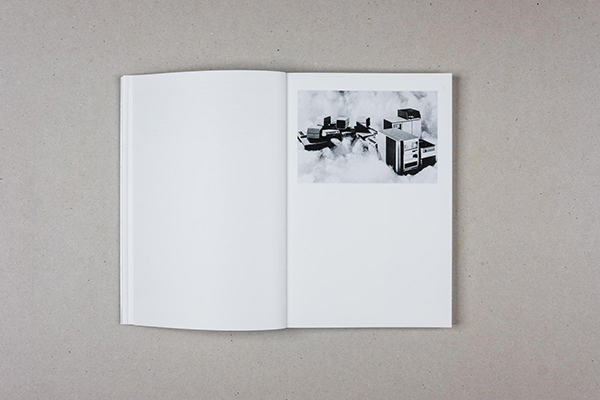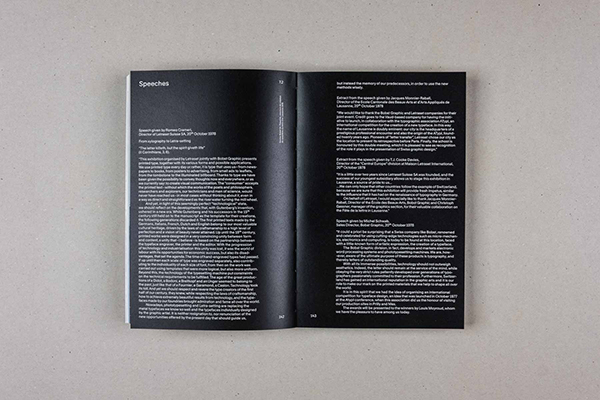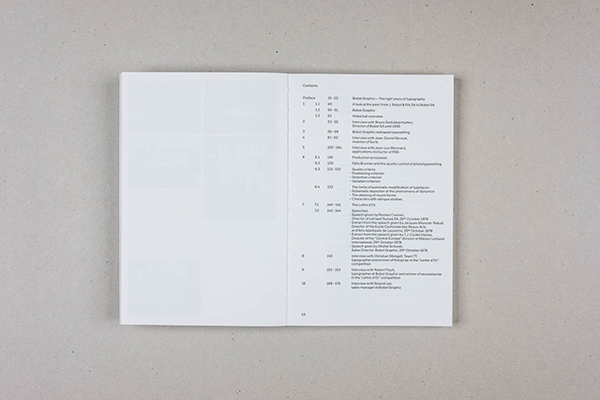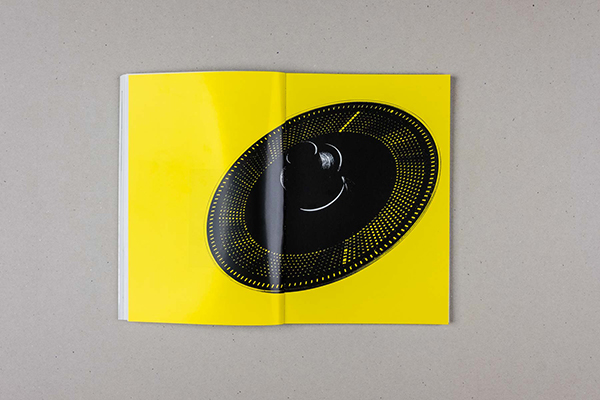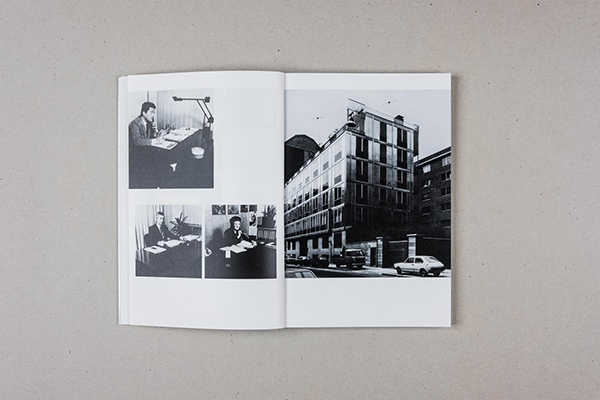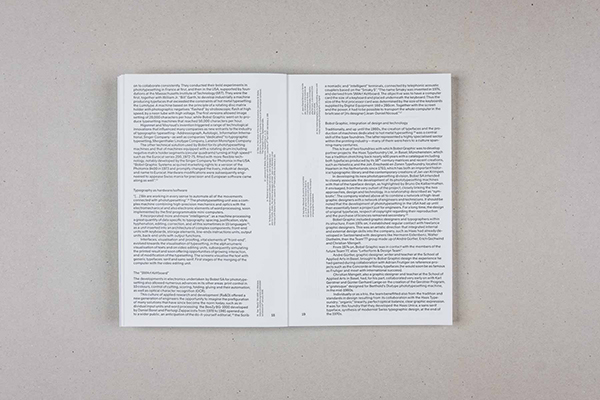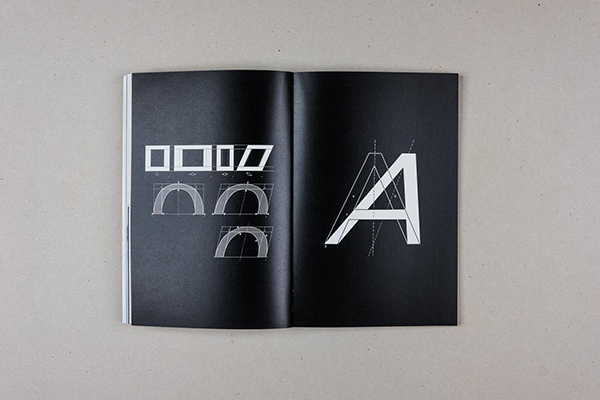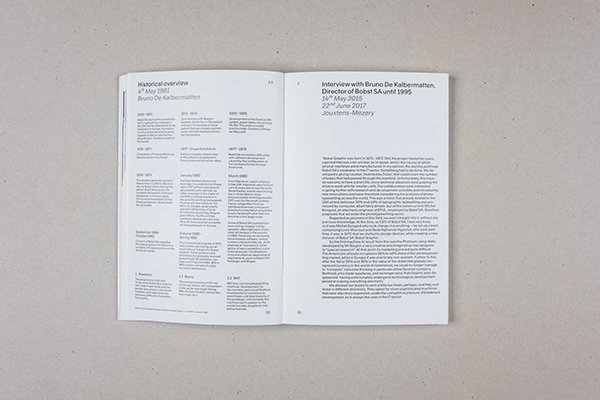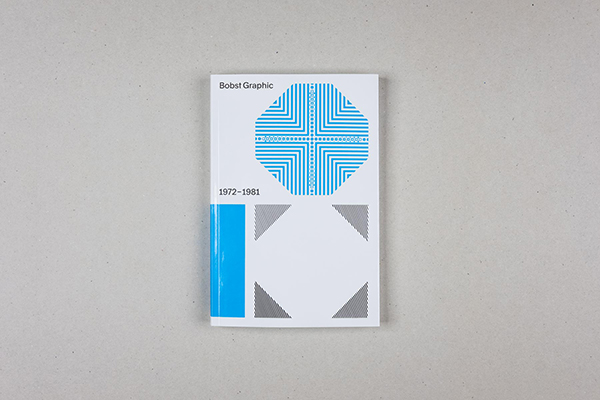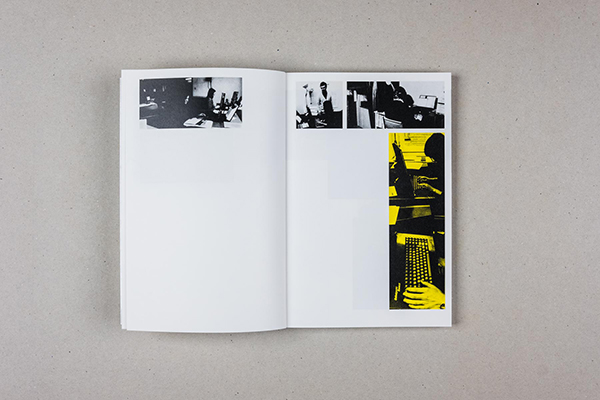
Bobst Graphic (E)
1972–1981
Der zweite Band der Reihe «Visuelle Archive» widmet sich der bislang unbekannten Firmengeschichte der Fotosatzpioniere von Bobst Graphic.
Anfang der 1970er-Jahre begann sich die Schweizer Verpackungsfirma Bobst S.A. zu fragen, ob sie mit einer einzigen Produktart für die Zukunft gut aufgestellt wäre. Das Lausanner Unternehmen, das bezüglich der Herstellungstechnologie von Verpackungen bereits sehr weit fortgeschritten war, entschied sich, Lichtsatzmaschinen auf den Markt zu bringen.
Das Unternehmen wollte diese neue Technik mit den Hightech-Möglichkeiten des Computers verknüpfen, um eine bessere Typografiequalität zu erreichen. Es wurde eine ganze Reihe von neuartigen Fotosatzmaschinen hergestellt, für die sich Bobst Graphic, eine Marke von Bobst S. A., die Patente von Hugonnet und Moyroud – den französischen Erfindern der Fotomontage – gesichert hatte.
Für die neue Technik wurden auch dank der Beteiligung einiger der besten Schriftdesigner des Landes, etwa Team 77, verschiedene Schriftfamilien entwickelt.
Fünf Jahre nach der Gründung geriet Bobst Graphic jedoch in finanzielle Schieflage und alle operativen Tätigkeiten und das gesamte Personal wurden an das US-amerikanische Unternehmen Autologic veräussert, bevor zwei Jahre später alle Geschäftsfelder vollständig in die Vereinigten Staaten verlegt wurden.
Die Geschichte von Bobst Graphic – seinerzeit eine Pionierleistung in der Entwicklung des Fotosatzes – ist nie in die reiche Historie des Schweizer Grafik- und Schriftdesigns einbezogen worden. Daher hat sich die Autorin Giliane Cachin entschieden, die faszinierende Geschichte mittels Interviews zu dokumentieren und zu teilen.
Zu Wort kommen Bruno De Kalbermatten, Jean-Daniel Nicoud, Robert Flach, Roland Jan und Christian Mengelt.